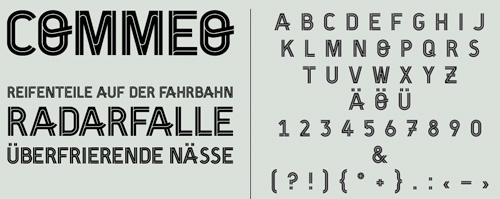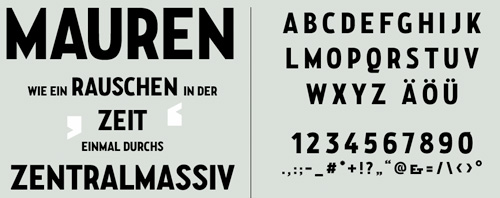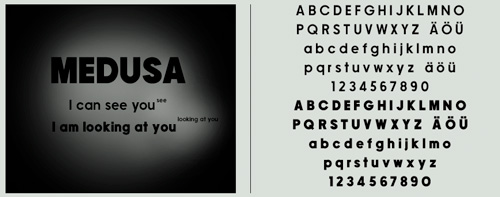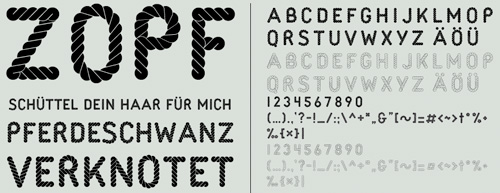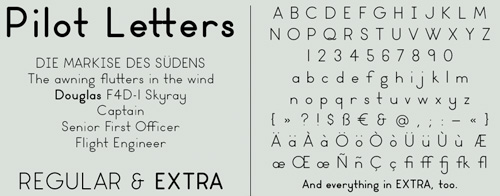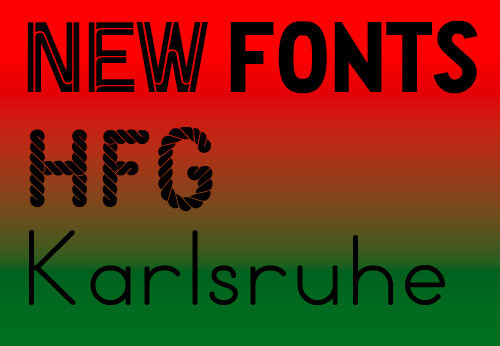
Die HfG Karlsruhe bietet einen bunten Haufen neuer Schriften an. Auf der Website
Im vergangenen Winter haben wir wieder einige neue Fonts veröffentlicht.
So hat Daniel Schludi nach der konstruiert-dekorativen PILOT LETTERS in 2 Schnitten nun sein neuestes Baby uns zugeschickt. MEDUSA kommt wie PILOT LETTERS mit Kleinbuchstaben aus dem Zeichenlabor. Der eindrucksvolle, langatmige Zeichensatz entstand während Daniels gleichnamigem Diplomprojekt und kostet 60 Euro.
Chris Spatschek beglückte uns mit einem neuen Schnitt für die beliebte ZOPF. Mit dem Konturenschnitt kann nun dekorativer und filigraner gearbeitet werden, auch 2-farbiges ist möglich. Die 20 Euro, die der Font kostet, beinhalten nun beide Versionen.
COMMEO ist eine standfeste, detailverliebte illustrative Schrift von Claudia Löffler. Ebenso wie die Zopf ist die Schrift beim Type-Design Seminar von Rothenberger/Herrmann/Varone/Schatz entstanden.
Peter Stahmer zeigt nach einer dekorativen und einer Rasterschrift nun seinen ersten klassischen Schriftsatz: MAUREN heißt die formschöne Plakatschrift, die in Kürze auch mit Kleinbuchstaben zu haben sein wird. Das charakteristische "R" war zugleich auch der erste Buchstabe, den Peter vor einem Jahr in Spanien zeichnete, als er mit der Mauren anfing.